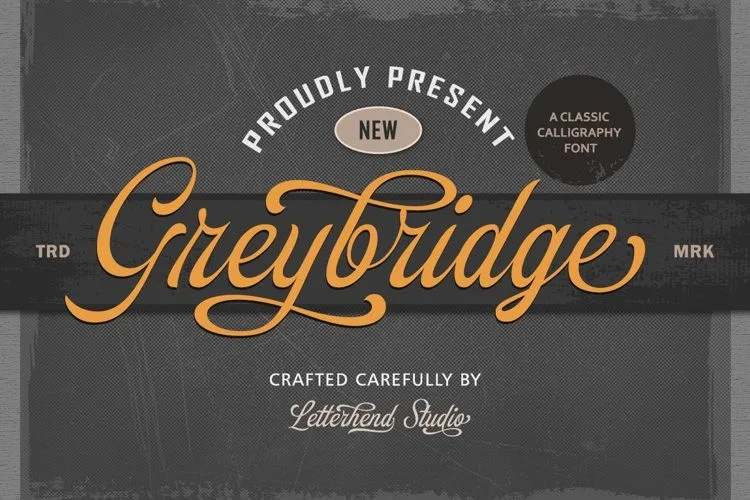
A Greybridge Font é uma escolha perfeita para qualquer projeto que busca uma mistura elegante de modernidade com o encanto nostálgico dos anos 60 e 70. Desenvolvida pela Letterhend Studio, essa tipografia script tem um aspecto retro bold que parece ter saído direto da época dos grandes discos vinil e das letras vibrantes nos anúncios de televisão da era pré-video. Esta font é perfeitamente adaptada para criar logotipos, além de se adequar perfeitamente a formatos formais como convites, rótulos, marcas de logótipo, revistas, livros, cartões de saudações e casamentos, embalagens, maquiagem e materiais de estação, novelas e etiquetas para qualquer tipo de propósito publicitário. Sua sofisticação e elegância combinada com um toque nostálgico o torna uma escolha ideal tanto para iniciantes quanto para profissionais experimentados na indústria da moda gráfica.